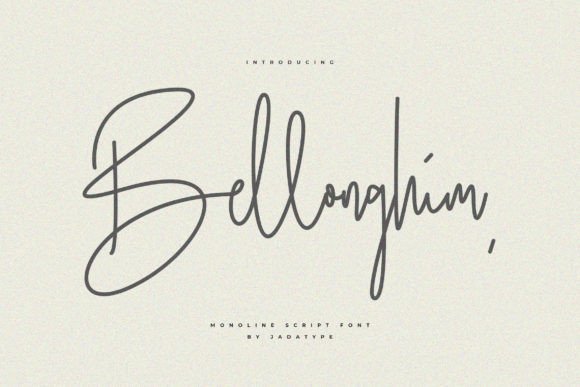
Bellonghim
Trouver les bons éléments de conception peut être un défi, mais Bellonghim propose une collection exceptionnelle qui rehausse instantanément votre travail.
Conçu avec précision, Bellonghim offre des vecteurs nets, une typographie fluide et une licence commerciale pour une tranquillité d'esprit.
Que vous créiez des produits POD (impression à la demande), des invitations de mariage ou des visuels pour les réseaux sociaux, Bellonghim est un choix idéal.